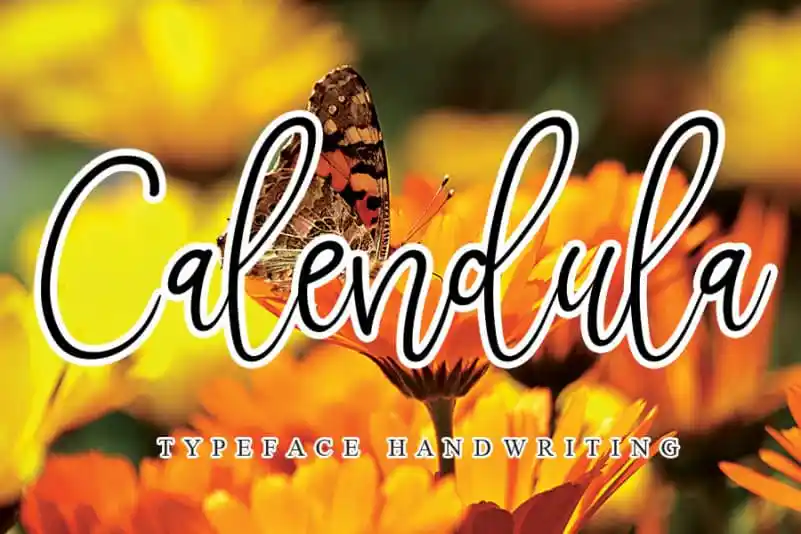
A Calendula Font é uma delicada e alegre fórmula de letra escrita à mão. Suavemente fluida e estiloosa, essa font irá dar vida aos seus designs, tornando-os únicos e encantadores. Ideal para criar cartões de convite elegantes ou frases bonitas no seu blog pessoal, a Calendula trará um toque suave e criativo à sua arte digital. Em uma era em que os conteúdos digitais precisam ser atraentes e personalizados, adicionar uma fonte escrita à mão como a Calendula pode fazer toda a diferença, tornando seus trabalhos ainda mais únicos e autênticos.